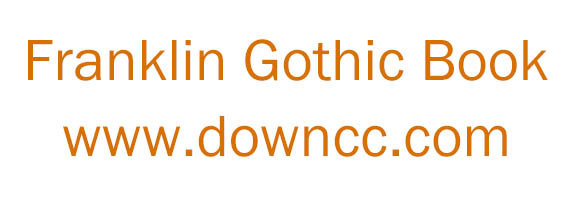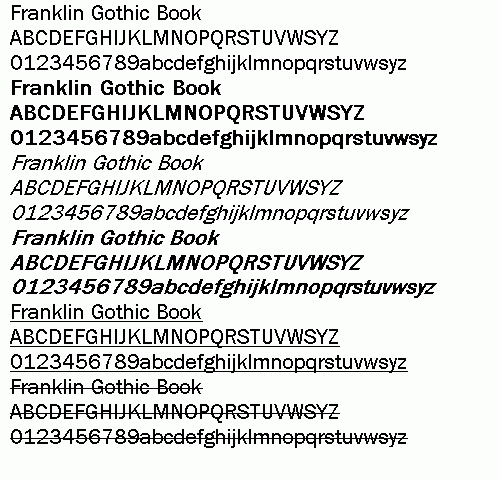
Franklin Gothic Book是一款非常正式的英文字體,字體中規(guī)中矩,非常的具有現(xiàn)代特色,需要這款字體的朋友趕緊來(lái)綠色資源網(wǎng)下載吧
Franklin Gothic Book相比于其他字體會(huì)顯得比較高大緊湊,是很多地方都可以使用的字體之一